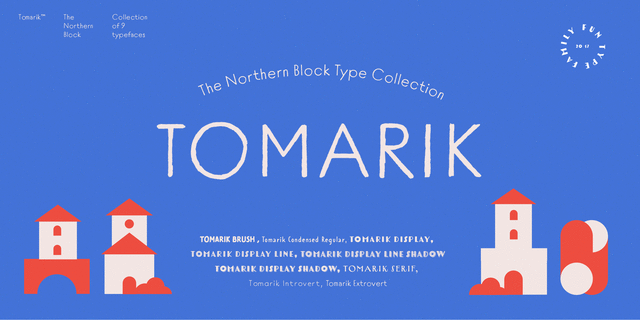
Закрытый геометрический гротеск, нарисованный ручкой или карандашом – часть яркой коллекции рукописных шрифтов Томарик. Игривое дополнение любого творческого проекта. Шрифтовой набор, собранный для работы по принципу «выбирай и смешивай», он предлагает большое разнообразие стилей и характеров. Томарик содержит девять различных начертаний с латиницей и кириллицей и включает функции OpenType, такие как верхние и нижние индексы и дроби. Шрифт разработала Мария Пигулевская в 2017 году. Tomarik™ является торговой маркой компании The Northern Block.
теплый, уютный, рукотворный, кустарный, самодельный, оригинальный, модный, живой, характерный, дружелюбный, детский, приятный, наивный, игривый, забавный, ламповый, милый, прикольный, мультяшный, вернакулярный, круглый, треугольный, позитивный, примитивный, лаконичный, понятный, ясный, городской, школьный
детский сад, отдых, игра, кафе, хюгге, инстаграм, город, игрушка, лагерь, школа, мультфильм, анимация, детская книжка, смузи, стикер, наклейка, канцтовары, карандаши, селфи Стилистика: